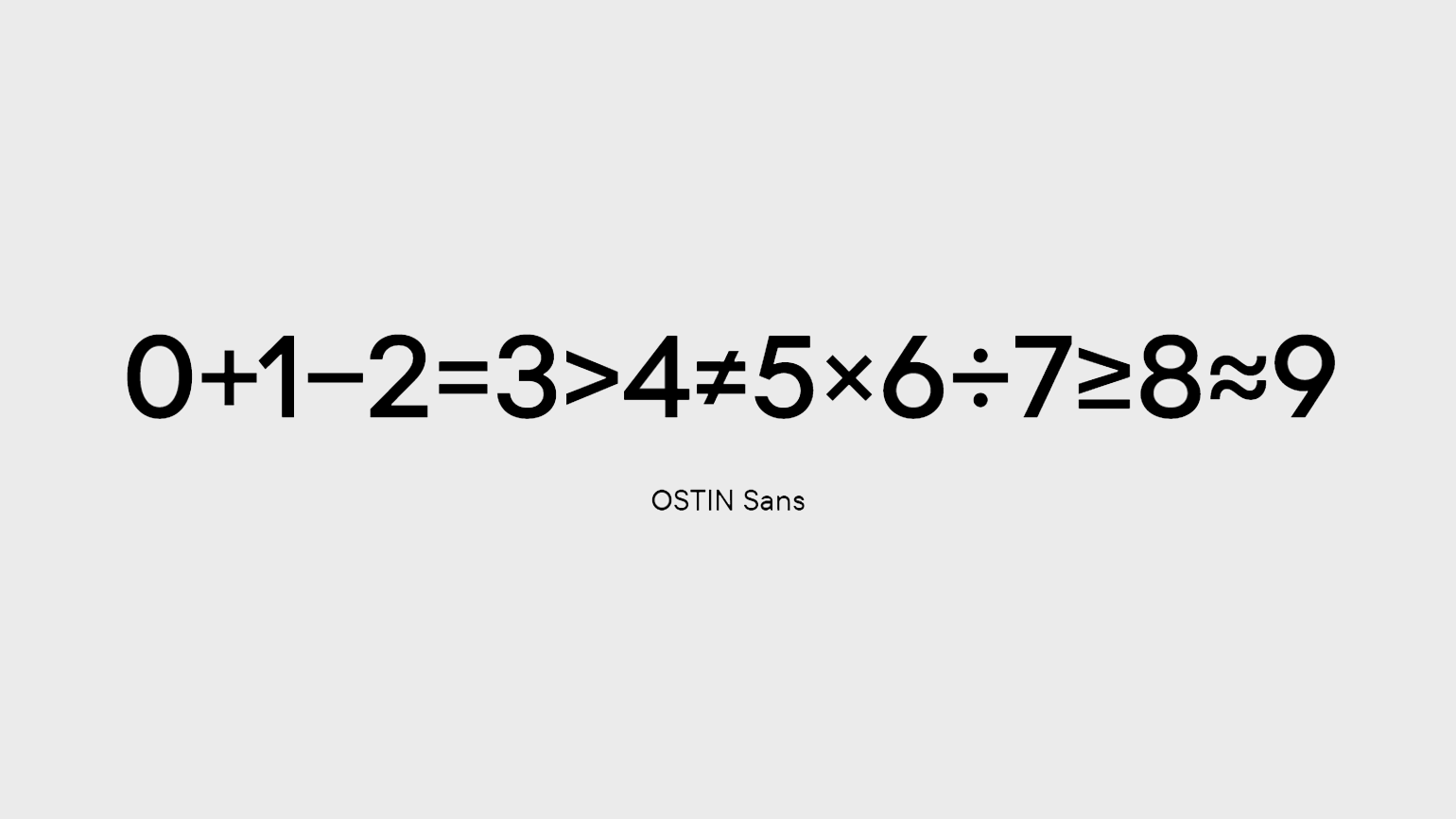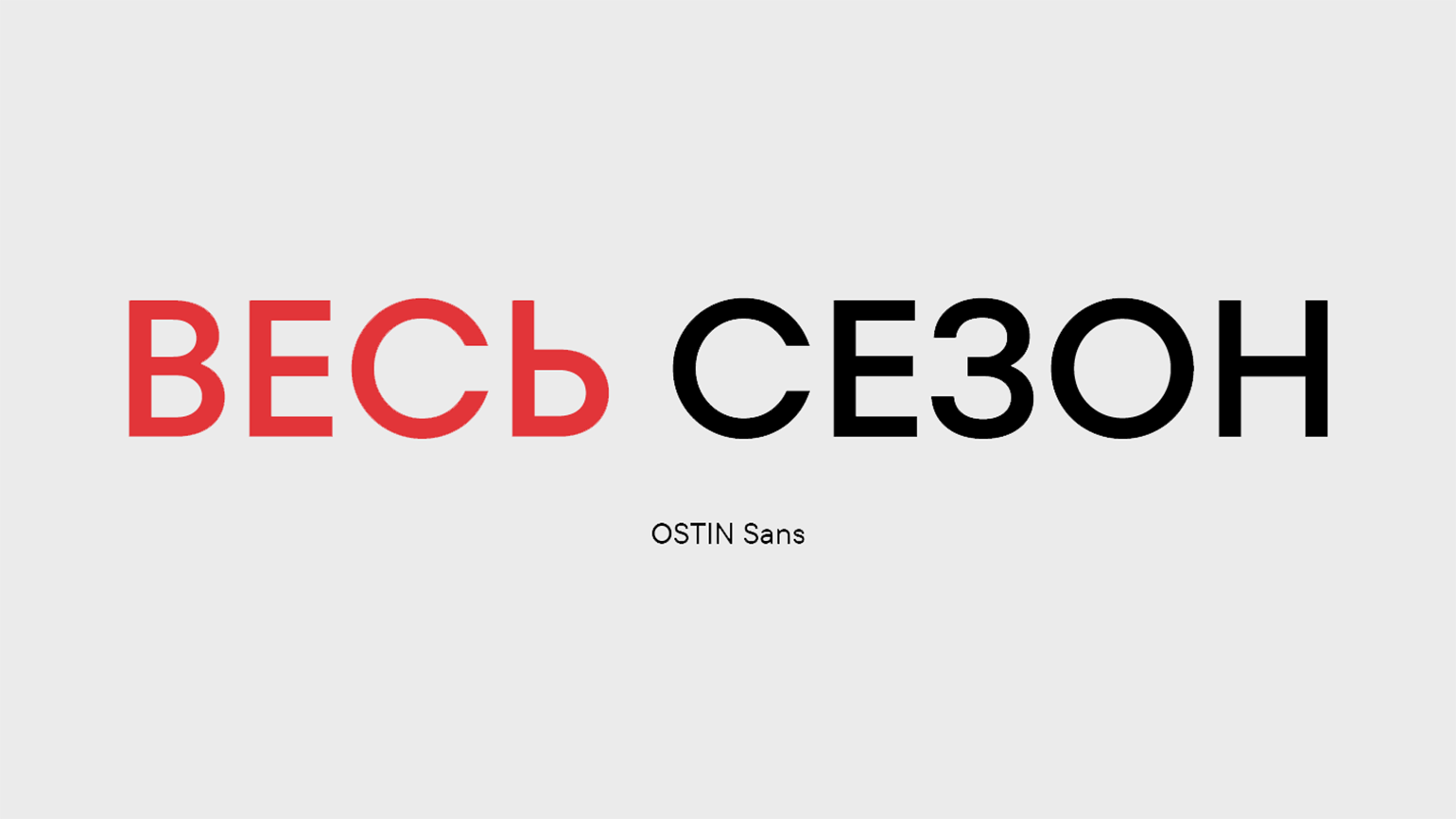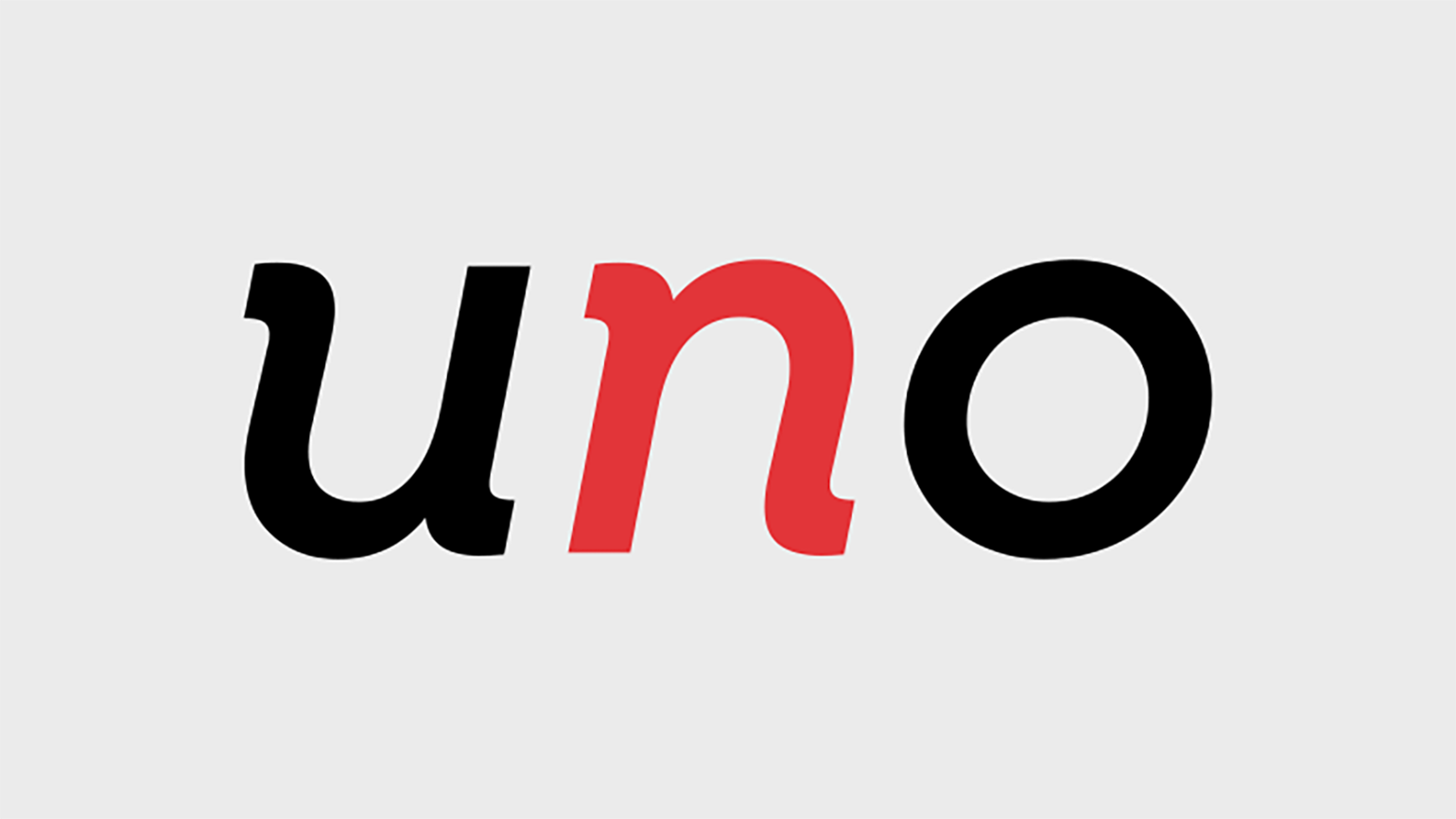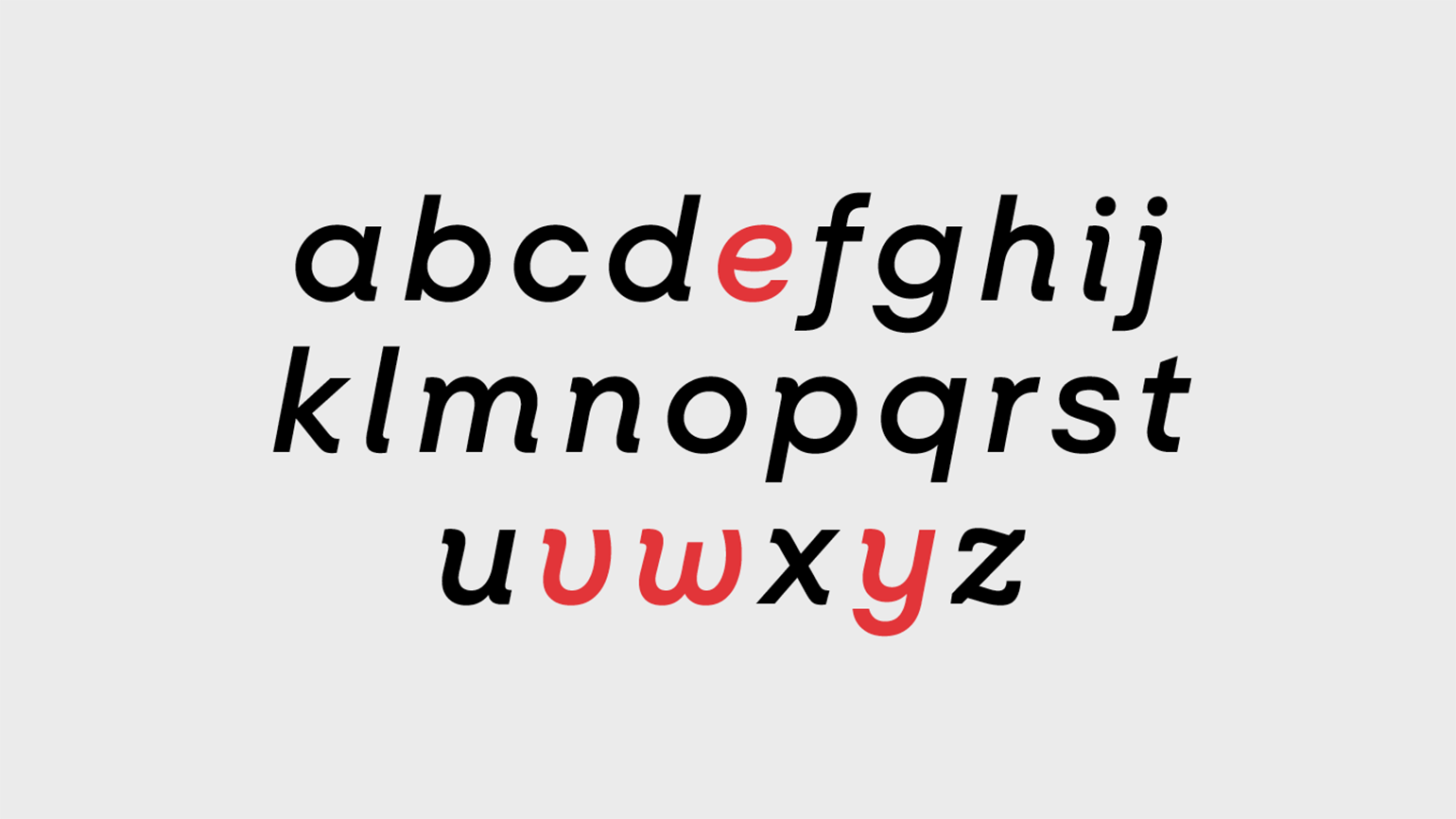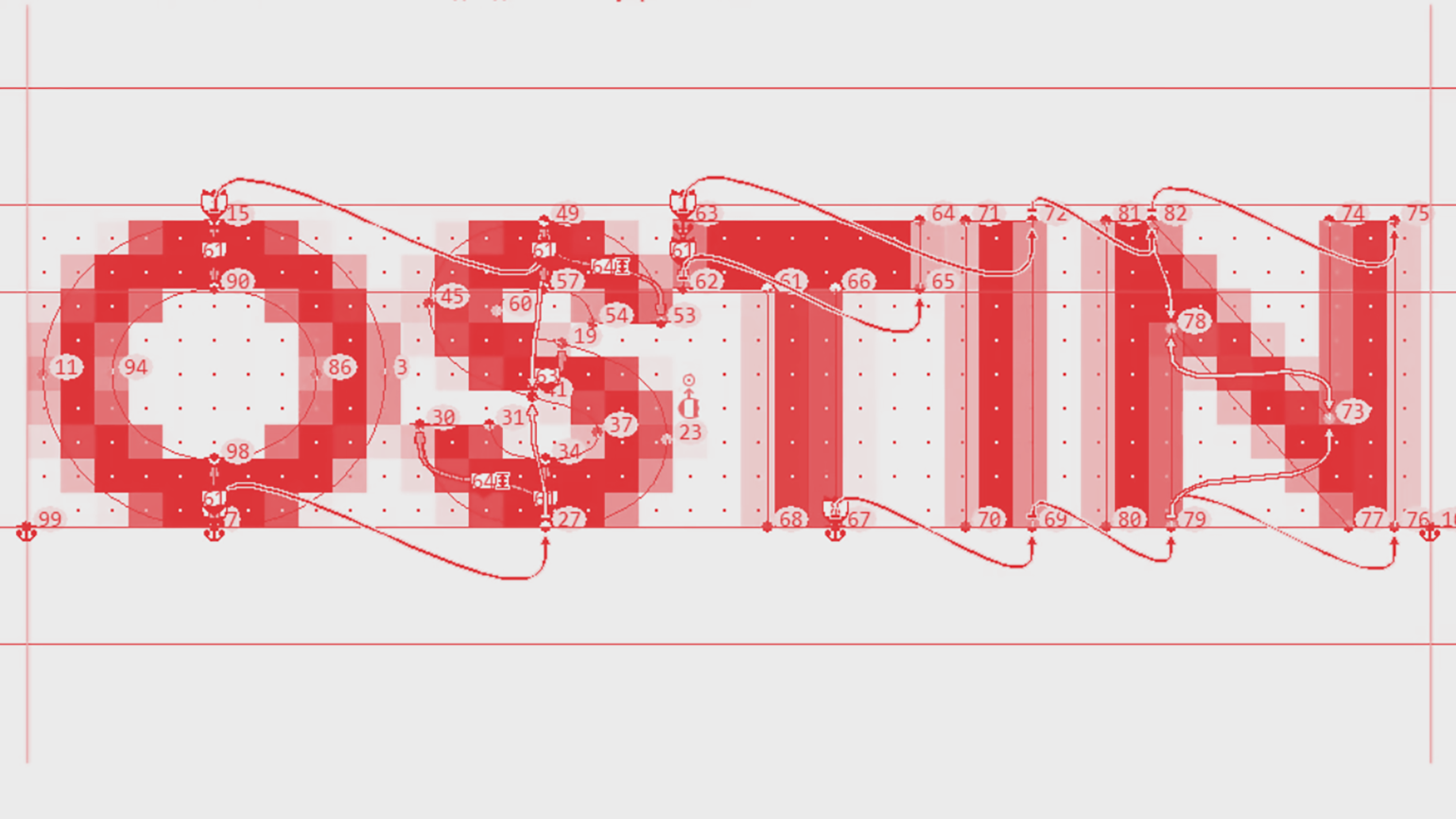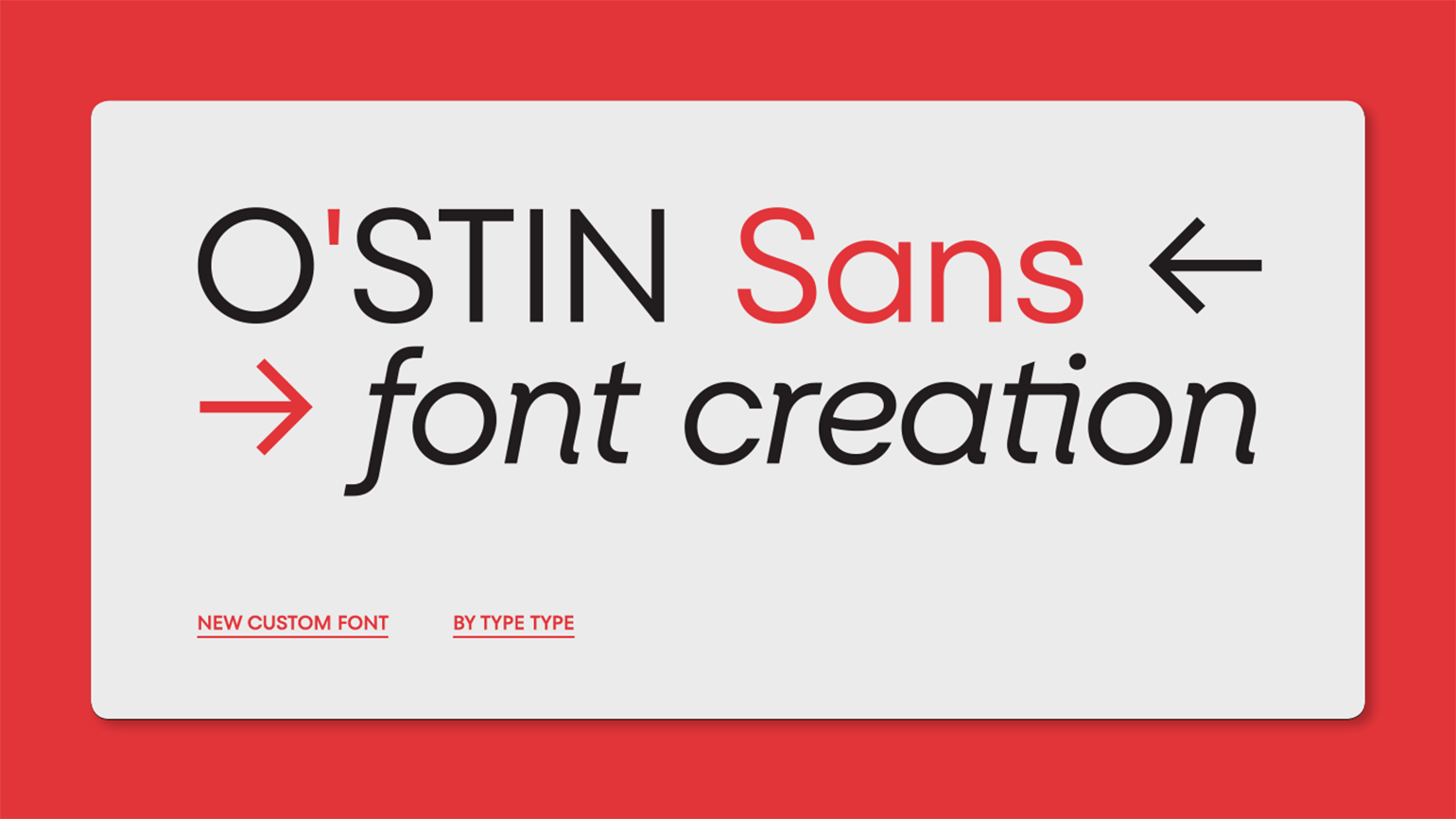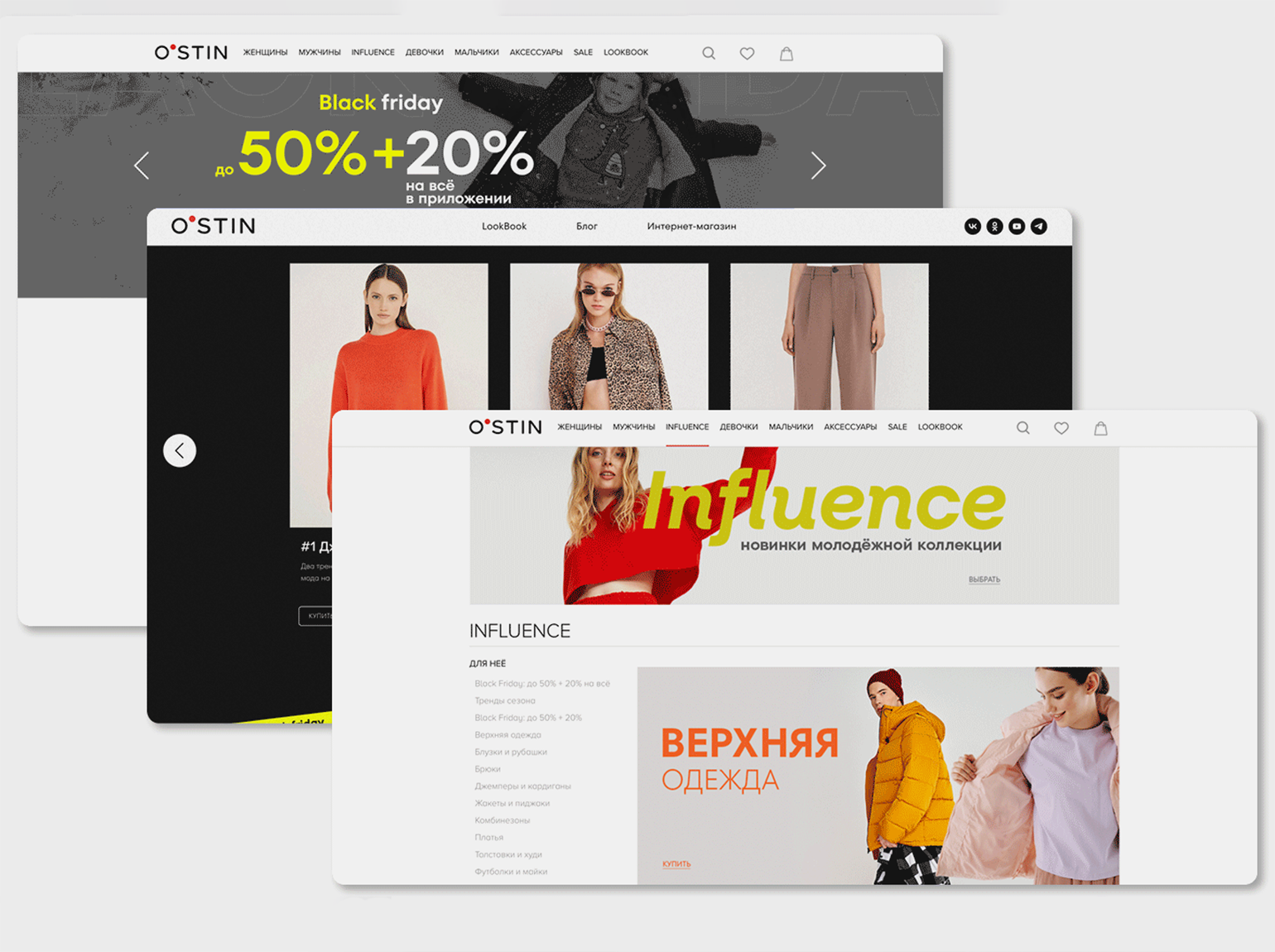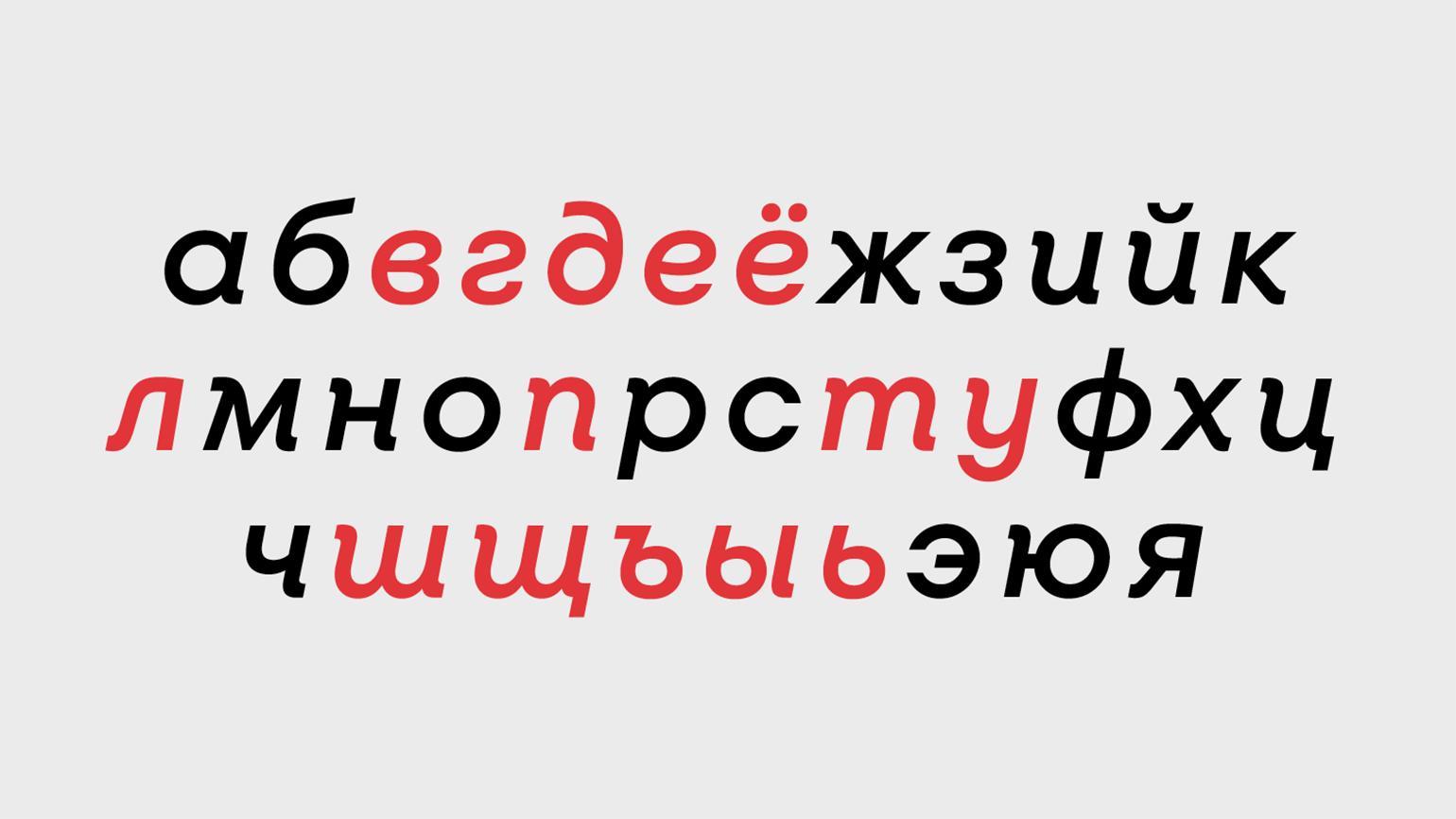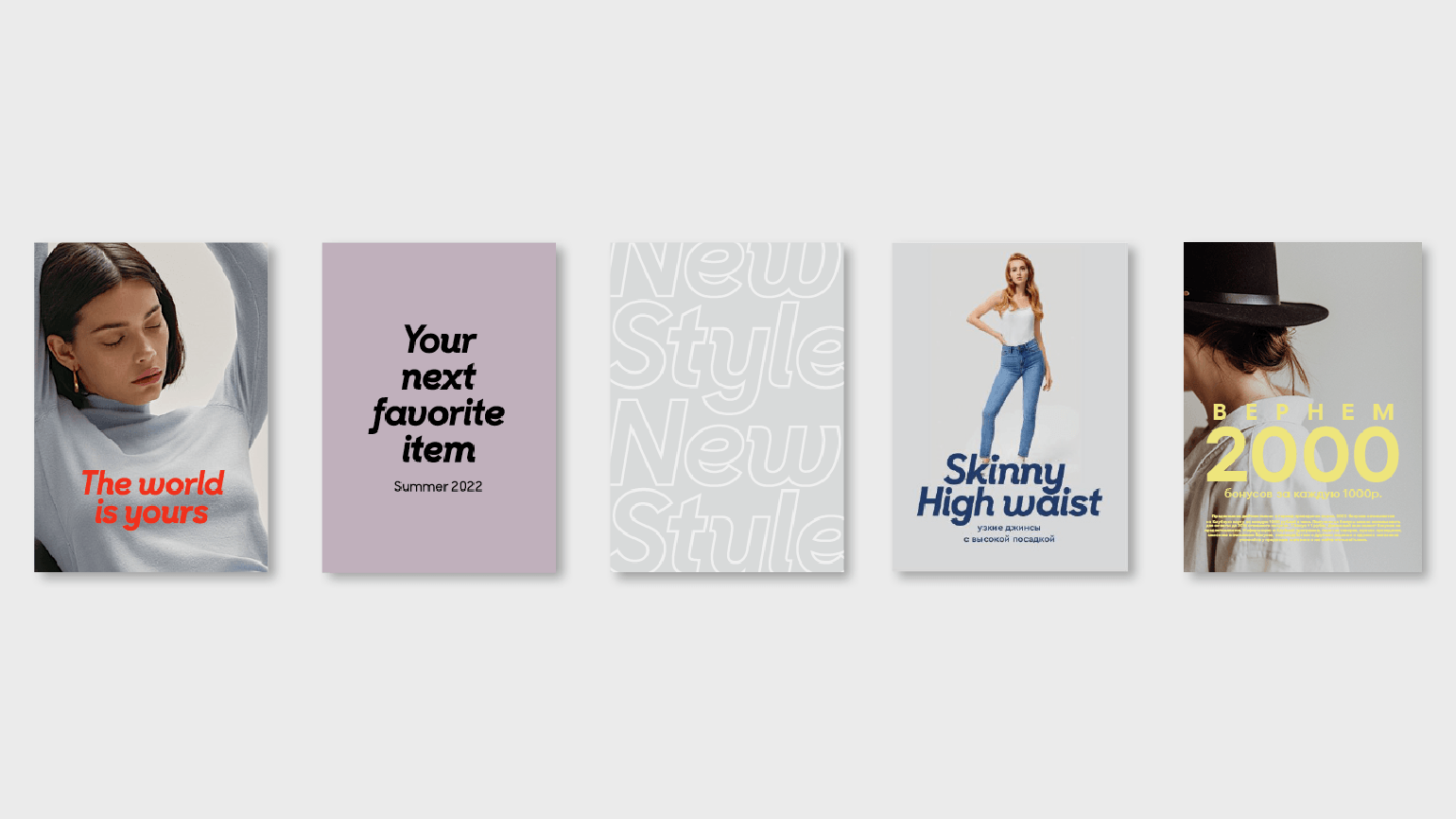
Студия TypeType обновила фирменный шрифт для бренда одежды O’stin
Работа заняла три месяца — это быстро для такого объёма.
Компания O’stin провела ребрендинг и обновила шрифт: задача дизайнеров заключалась в том, чтобы разработать прямые начертания для рациональной аудитории и италики (курсив) — для более эмоциональной.
Команда O’stin подготовила обновлённую концепцию бренда и обратилась к TypeType за подходящим шрифтом. Было два варианта —создать гарнитуру с нуля или взять один из уже готовых работ студии и адаптировать её. Выбрали второй путь — он быстрее и экономичнее, но всё равно требовал серьёзной работы.
Сначала команда TypeType провела исследование: как ведут себя конкуренты, какие шрифты у кого используются, что работает на рациональную аудиторию, а что — на эмоциональную. Выяснилось, что сам факт наличия фирменного шрифта уже делает бренд ближе к эмоциональному сегменту. А если этот шрифт — геометрический гротеск, да ещё с италиками, то эффект усиливается.
В итоге выбрали шрифт TT Fors — его восприняли как надёжный, современный и довольно универсальный. Гарнитура должна быть не только красивой, но и удобной. Её должно быть легко использовать в макетах, на сайте и в приложениях, без серьёзной переработки верстки.
Поэтому шрифт получил 4 прямых и 4 курсивных начертания. Его название изменили с TT Fors Medium на Ostin Sans SemiBold. Кроме того, дизайнеры подкорректировали разрядку, цифры и математические знаки, немного смягчили пропорции букв, чтобы они лучше смотрелись в реальных макетах, и добавили фирменные графические детали, чтобы шрифт стал более узнаваемым.
Создание курсивов потребовало отдельных усилий. Команда рисовала их с нуля, ориентируясь на характер основного шрифта. Особенно много внимания потребовалось для строчных букв. В них добавили плавные переходы и изменили форму, чтобы всё выглядело гармонично.
Чтобы сделать гарнитуру завершённой, в прямые начертания добавили несколько выразительных элементов из курсивов — например, более мягкие диагональные штрихи. Это связало два стиля в единое семейство.
Дальше началась техническая часть: дизайнеры настроили вертикальные параметры, чтобы новый шрифт легко заменял старый, и провели ручной кернинг (то есть настройку интервала между буквами), чтобы текст был читаемым в любом размере. А ещё команда настроила хинтинг, чтобы шрифт чётко отображался даже на экранах с невысоким разрешением.